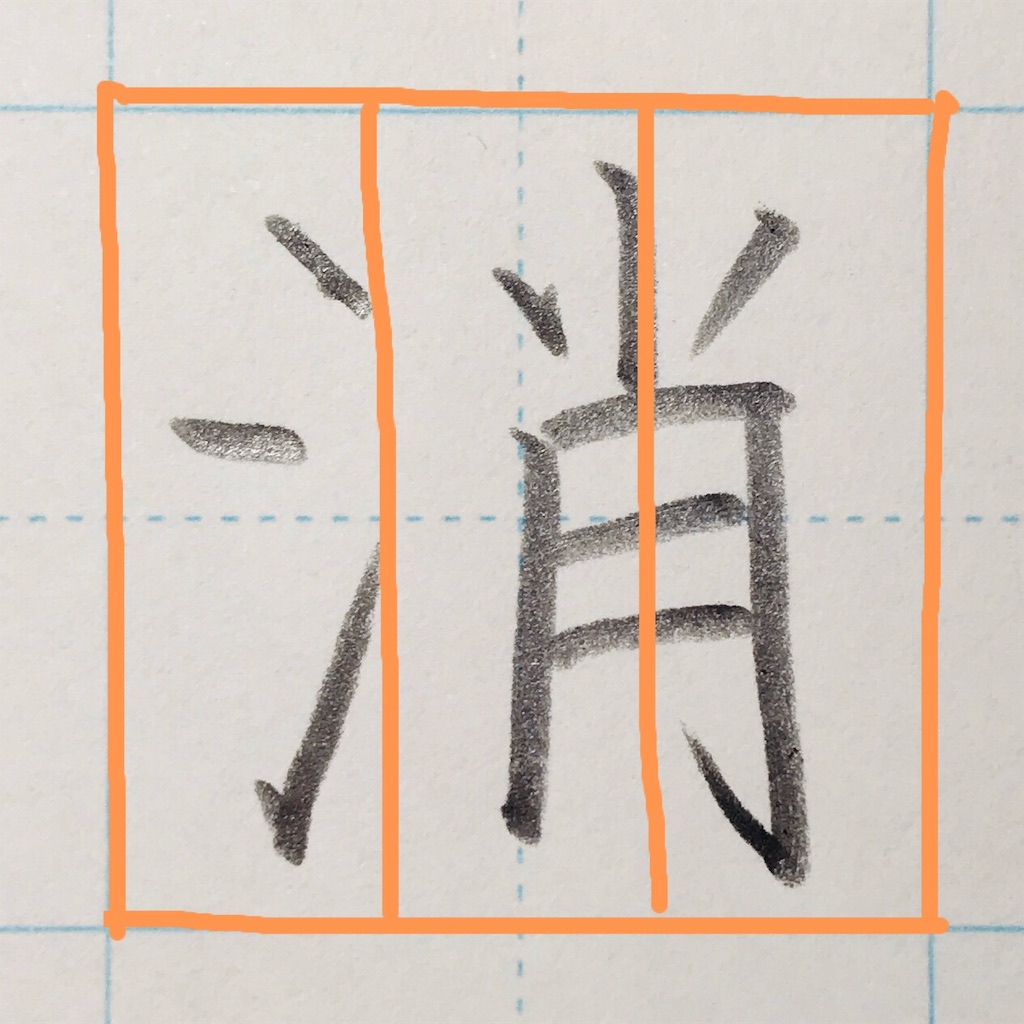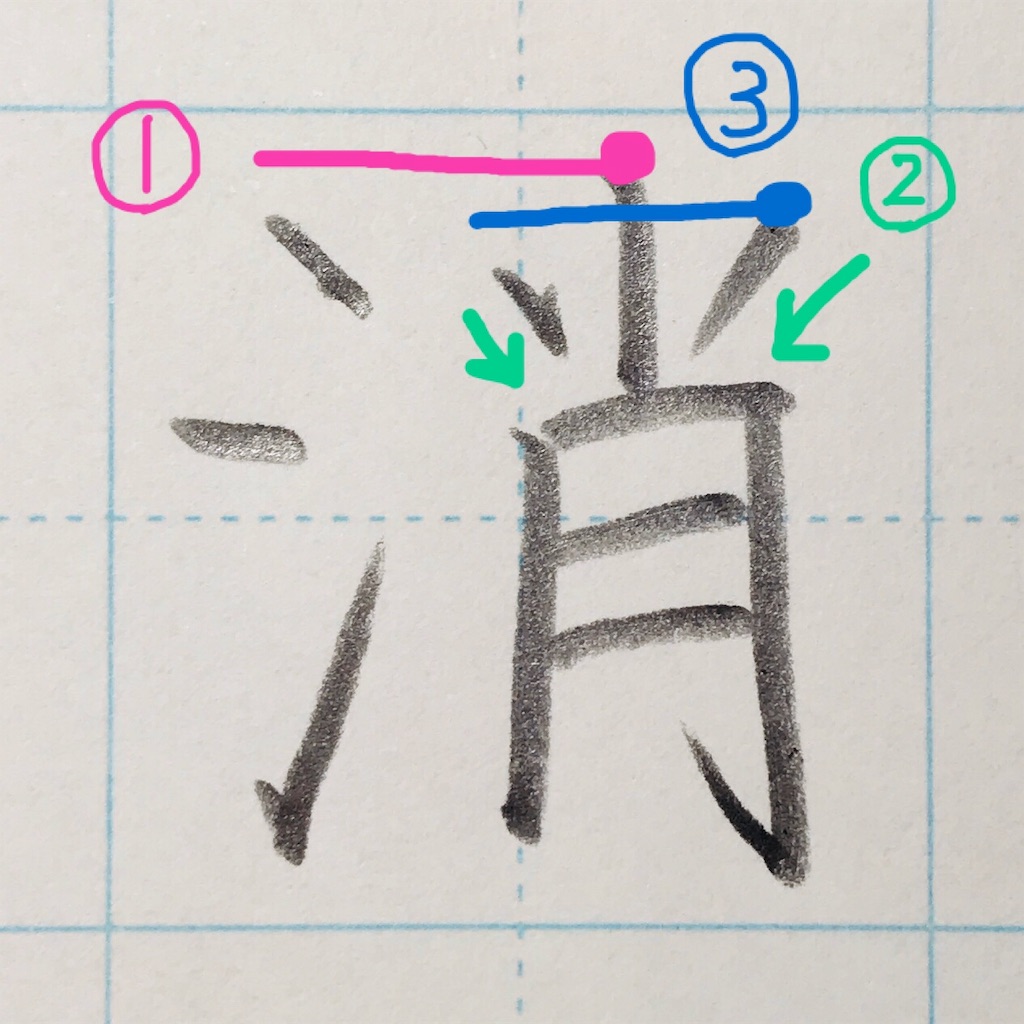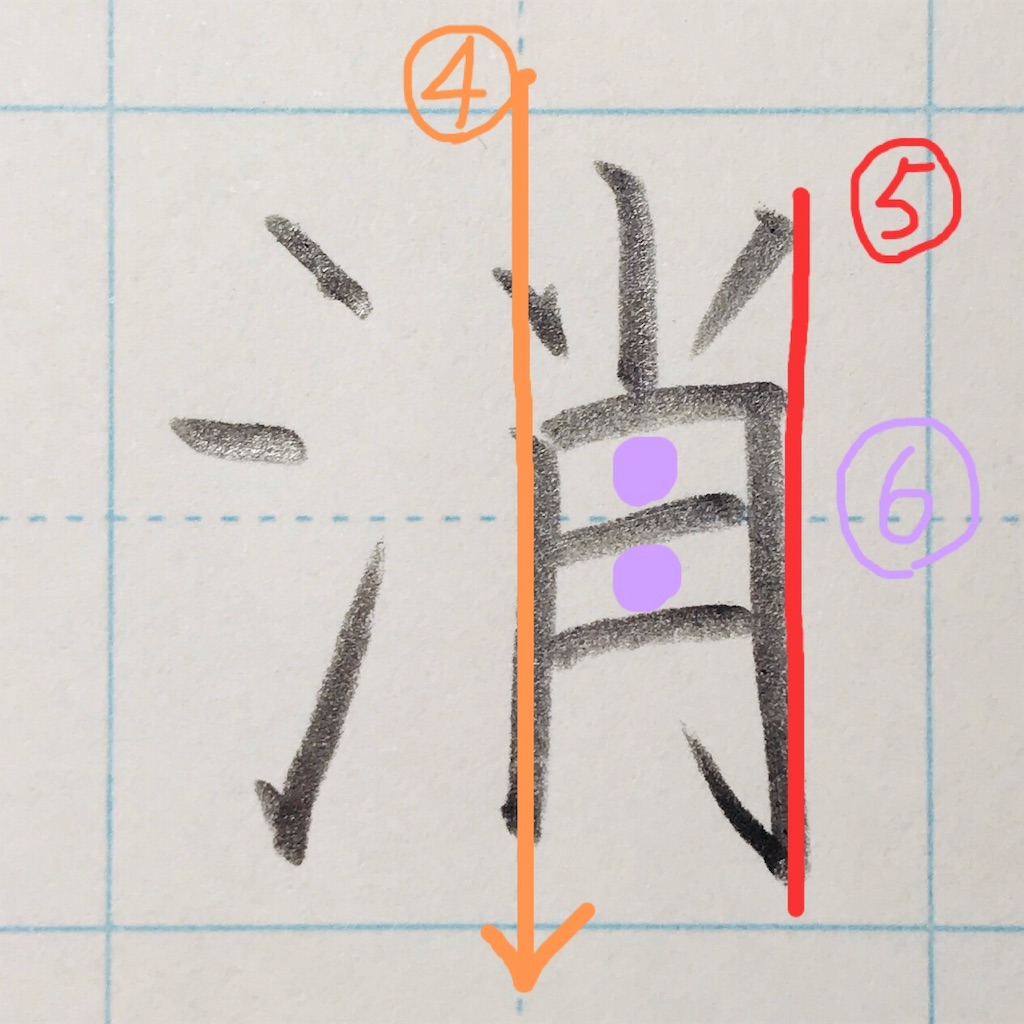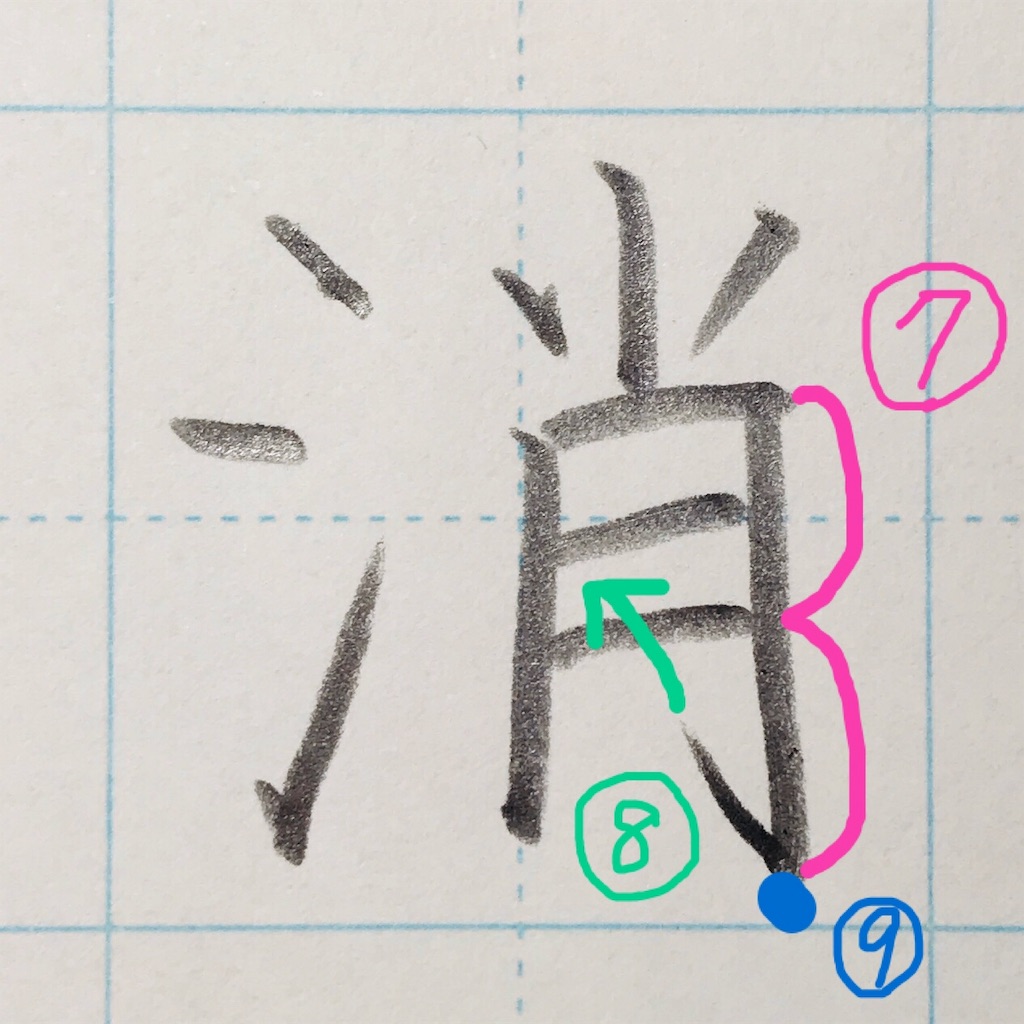
今回は「消」の書き方を解説します。
「消」のポイント
①4画目はさんずいより少し高く。
②5、6画目はそれぞれ45°くらいで内側へ向かう。
③6画目は5画目より少し高く。
④5画目のはじめと7画目の縦画が中心になる。
⑤右端はだいたいそろえる。
⑥同じ間隔に。
⑦10画目の横画を基準に、上下同じ長さになるように調整する。
⑧ハネは、次の画に向かうようにすると◎。
⑨この角を一番低くする。